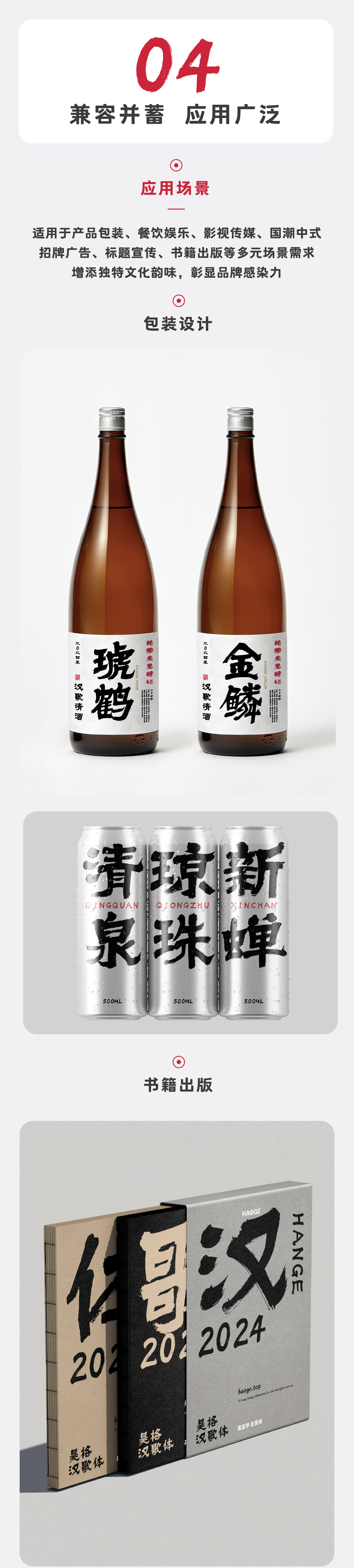
昊格汉歌体
昊格汉歌体,淳朴古雅,雄浑潇洒,昊格汉歌体以手书书法之韵,展现独特魅力。在结构设计上,汲取隶书之端庄、稳健,字形宽广而不失匀称,融合严谨与放达于一体,尽显野逸风范。笔形方面,继承蚕头燕尾之古典风貌,融入创新思维,笔锋蕴含力量,流畅展现速度与灵动。细节处理上保留毛笔独有的笔触之美,丰富的装饰性与视觉张力并存,展示深邃的艺术表现力。 适宜于多元化应用场合,如食品包装、餐饮品牌形象、影视节目制作、中式传统文化产品、商业招牌广告、标题宣传及书籍出版等,皆能增添独特文化韵味。字体覆盖 GB/T 2312-1980 编码字符集中的全部6763个汉字。除基础拉丁字母外,覆盖欧洲、非洲、亚洲、大洋洲、南美洲各种语言所需的字符共211个,可支持 90 余种语言,包括英语、法语、德语、西班牙语、芬兰语。支持阿拉伯数字、大小写罗马数字,以及其他 4 种样式的数字序号①⑵⒊㈣。包含标点和其他各类符号共 200 余个。商业用途
昊格汉歌体字体介绍